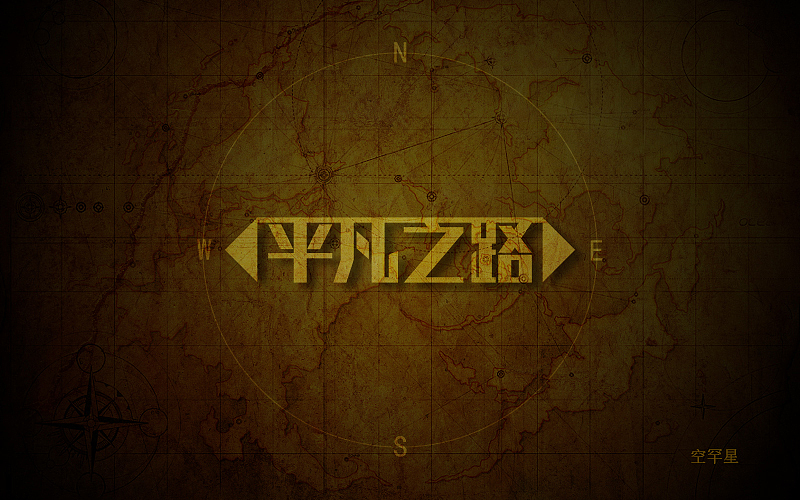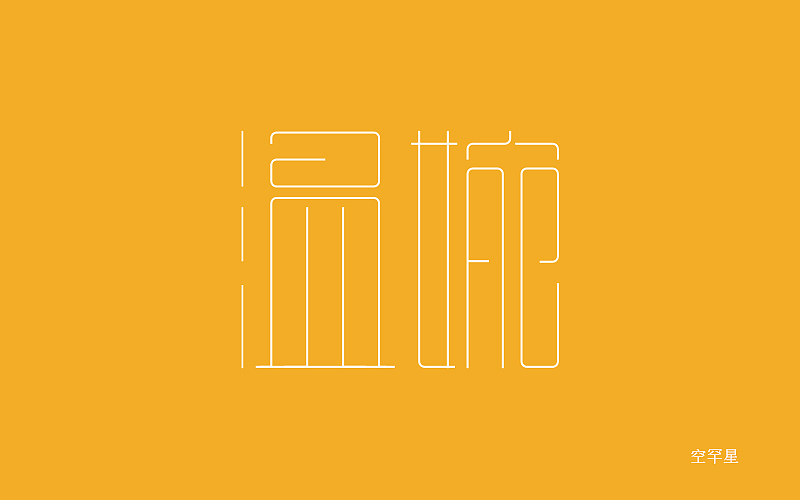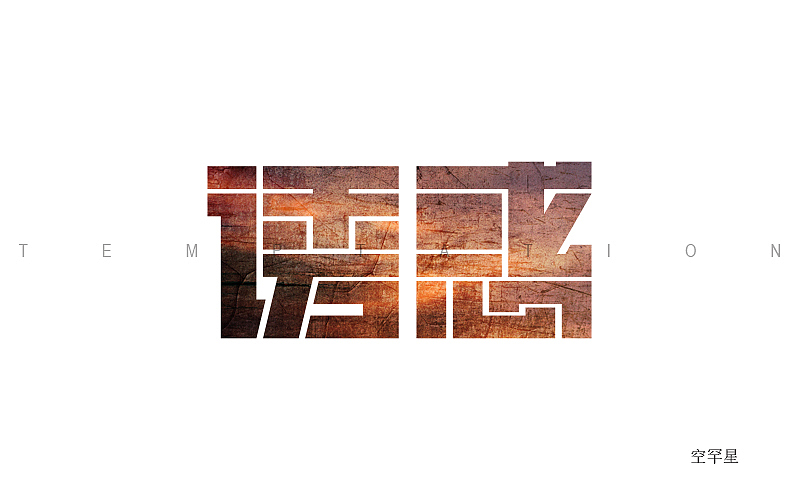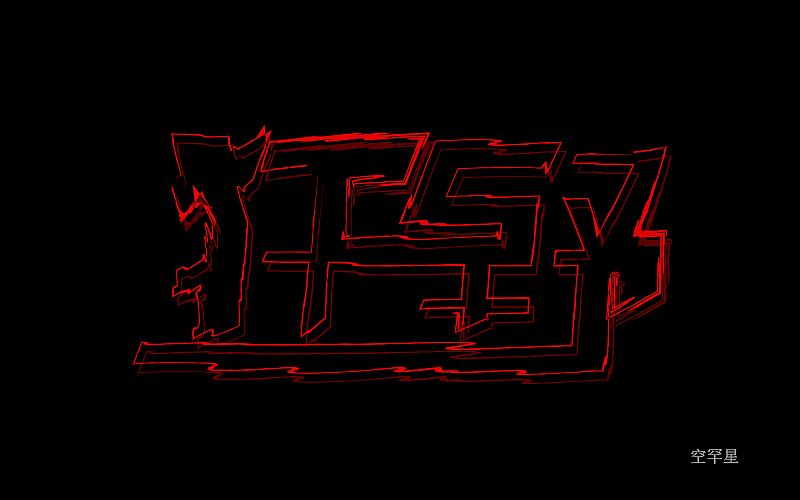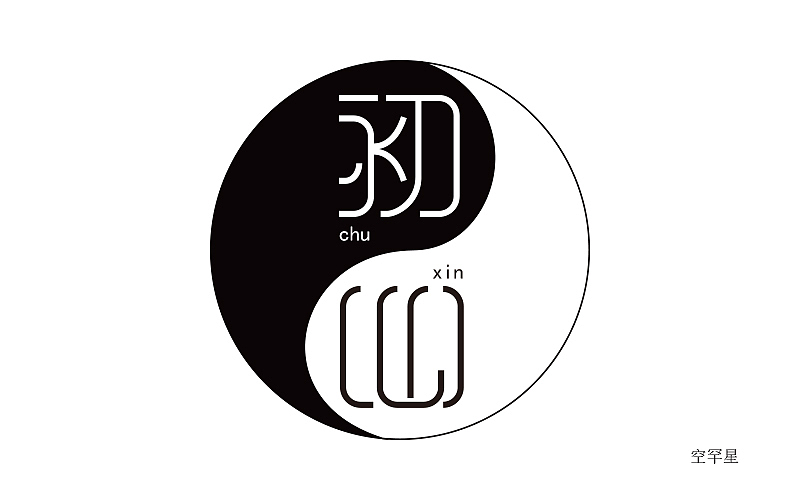
【字体帮】第一批落榜作品合集
空罕星
至今为止,参加了十期字体帮字体设计,其甜酸苦辣的创作过程,让我收益良多,虽远远未能入兵克老师的法眼,但通过对每天上榜字体的比较,其差距一目了然。
十期个人总结:
1、突出了本人对字形结构认识不足的问题。
2、突出了本人字体设计上创意不足的问题。
3、突出了本人对版式方面的不足,提交作品画面略显单调。
好多问题啊。。。。。。。。。。。。。。。。。。。。。。